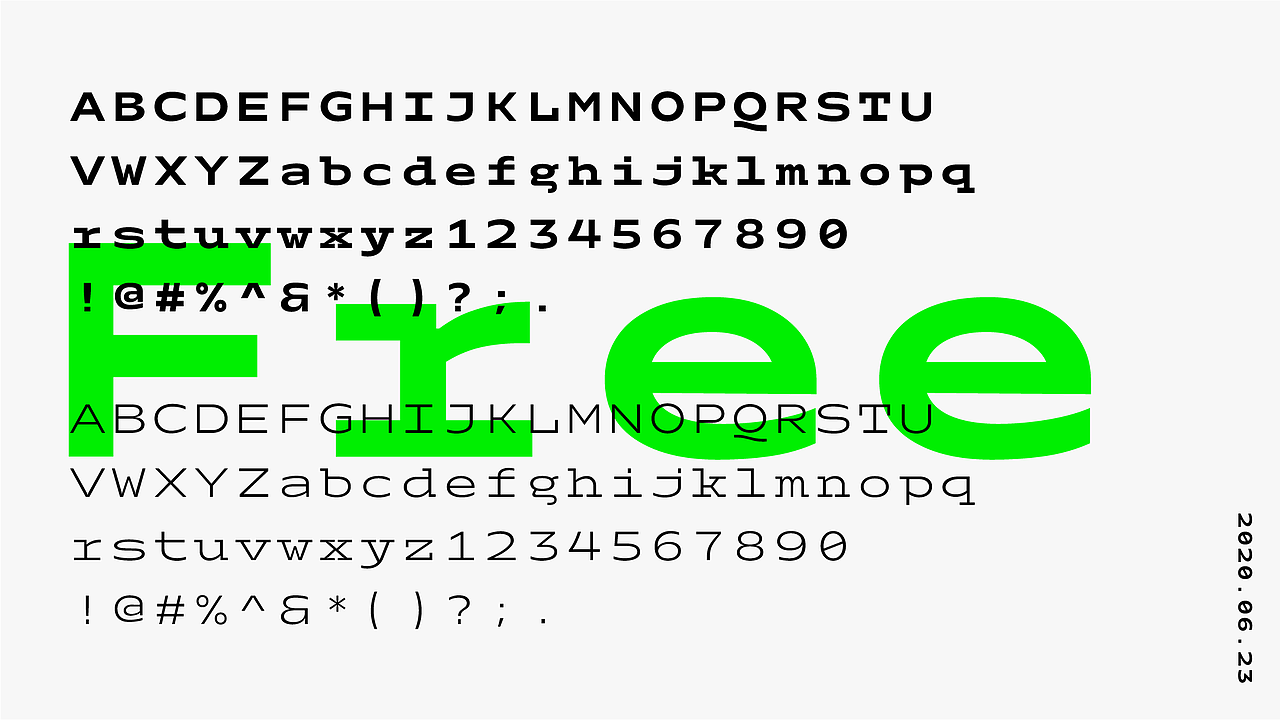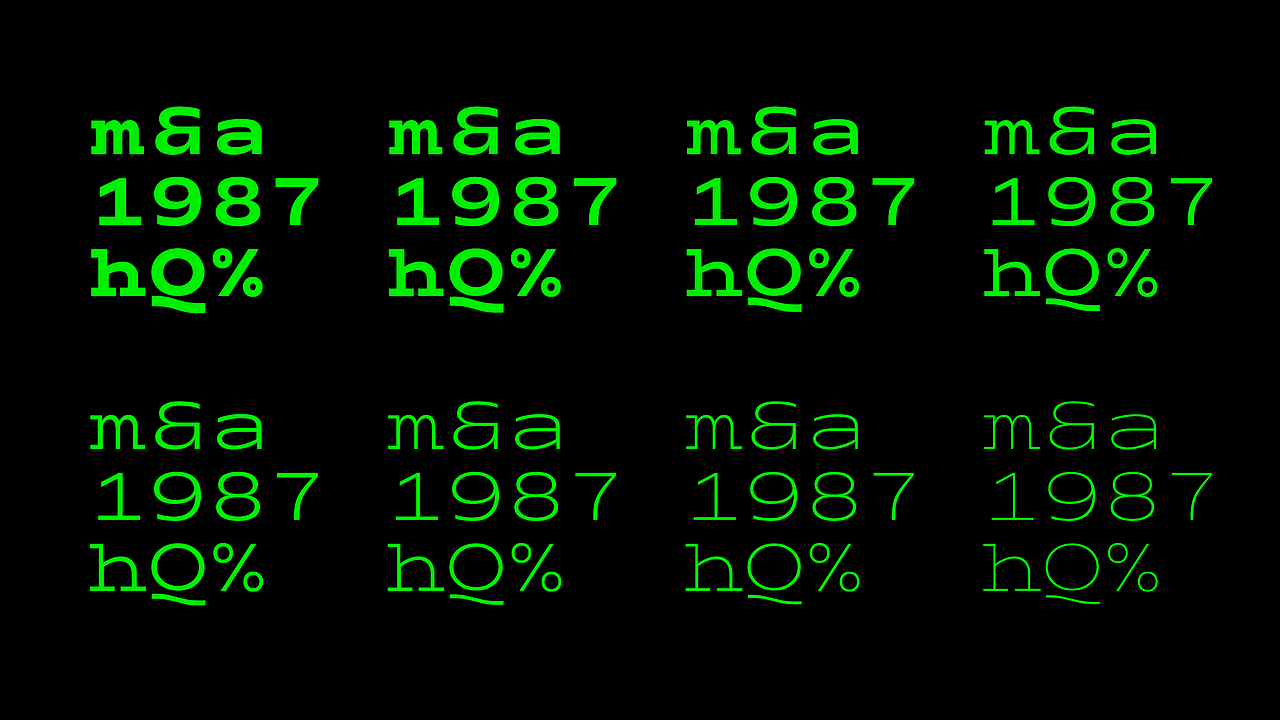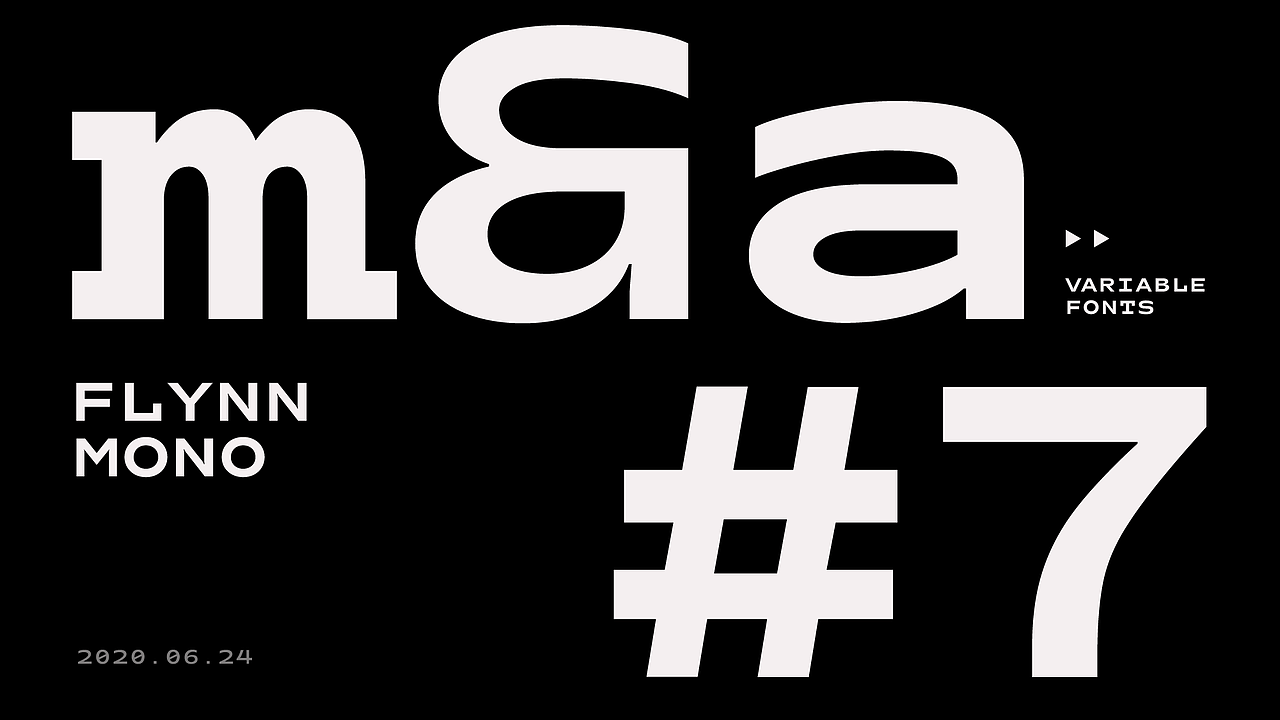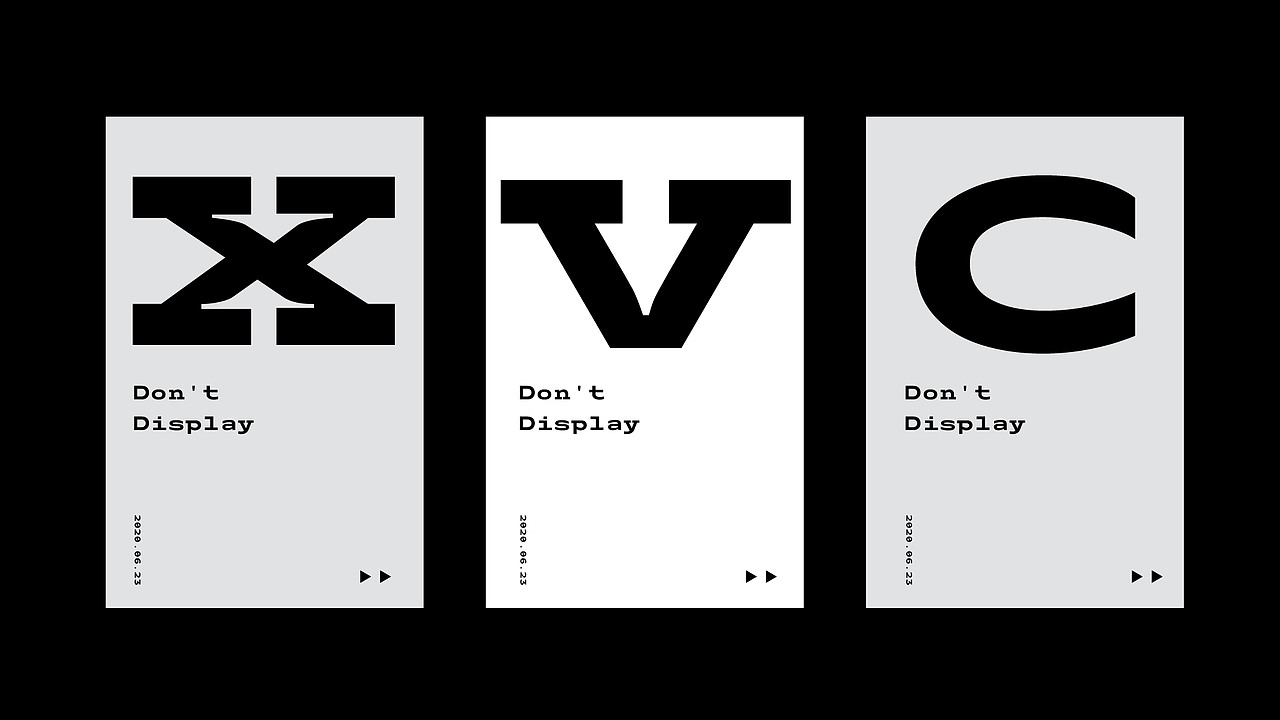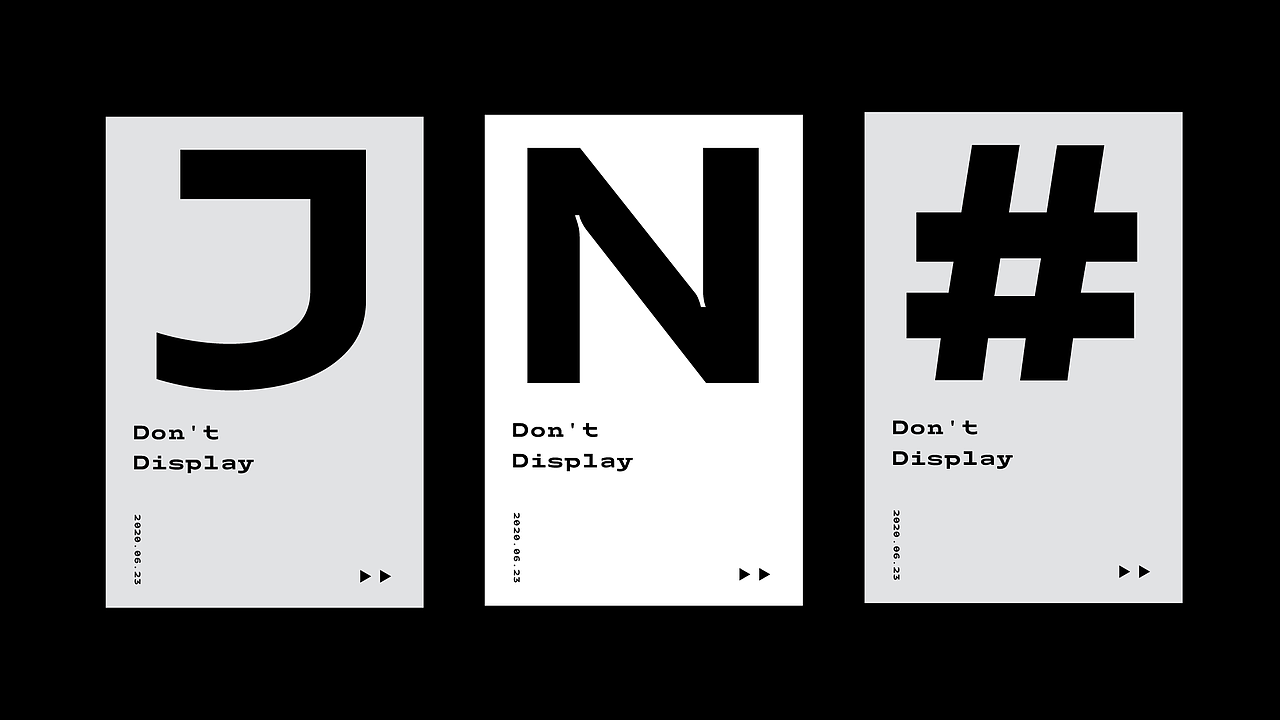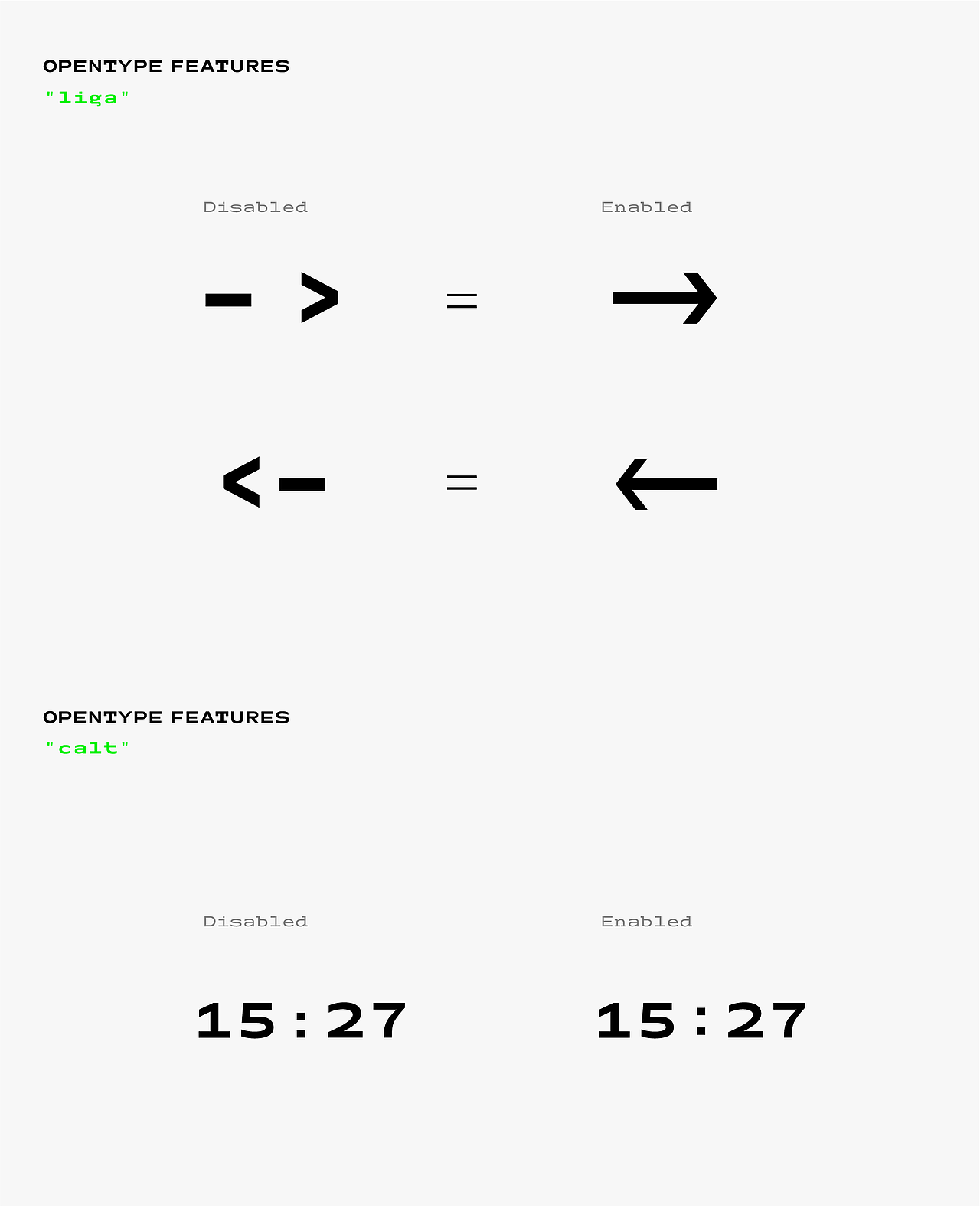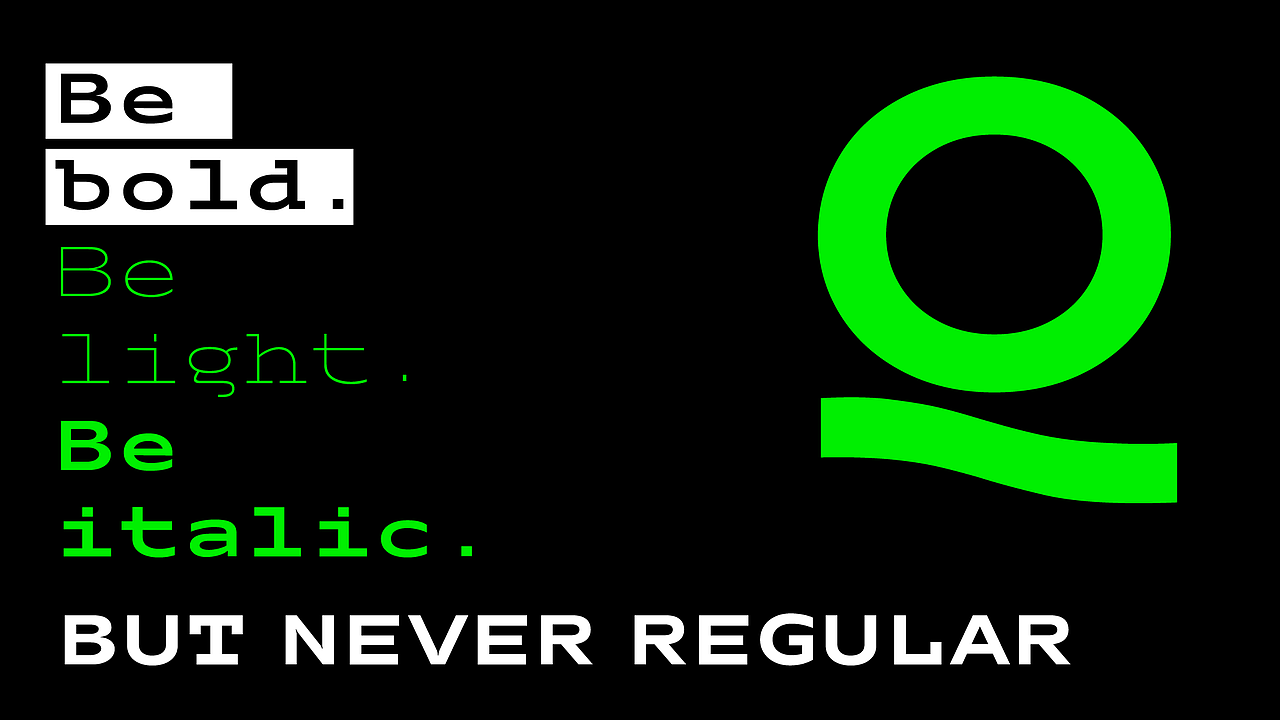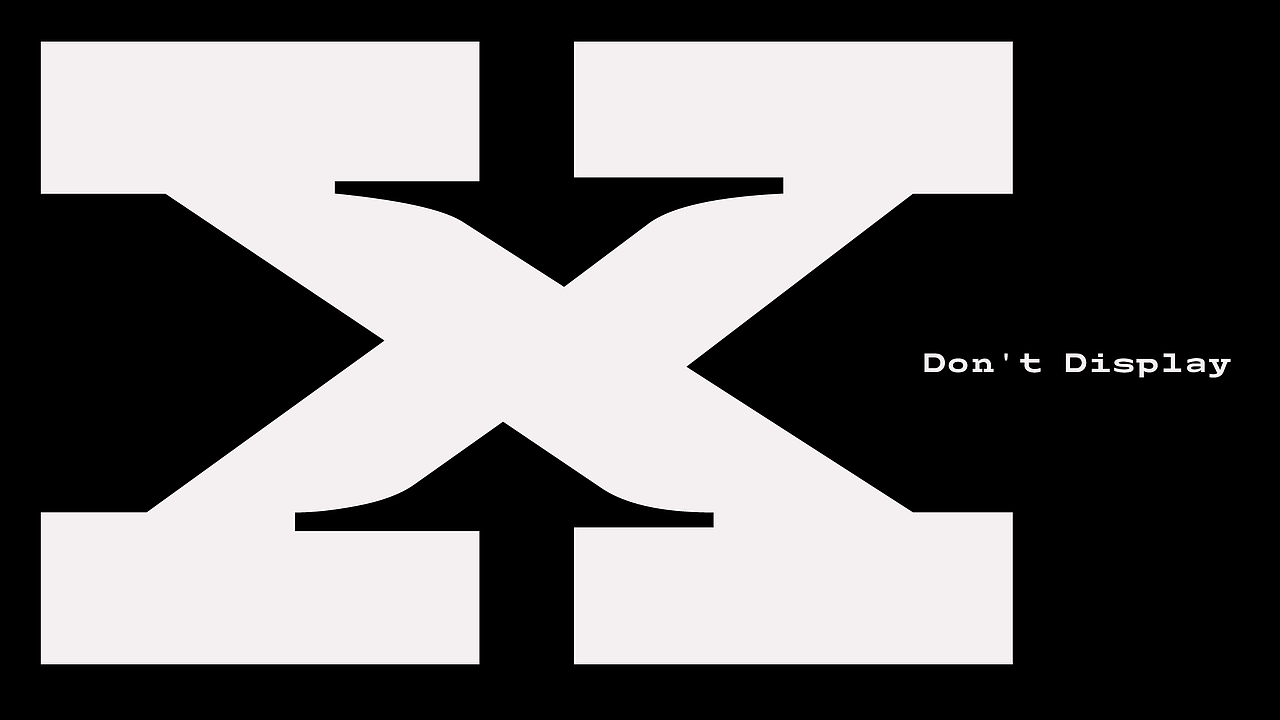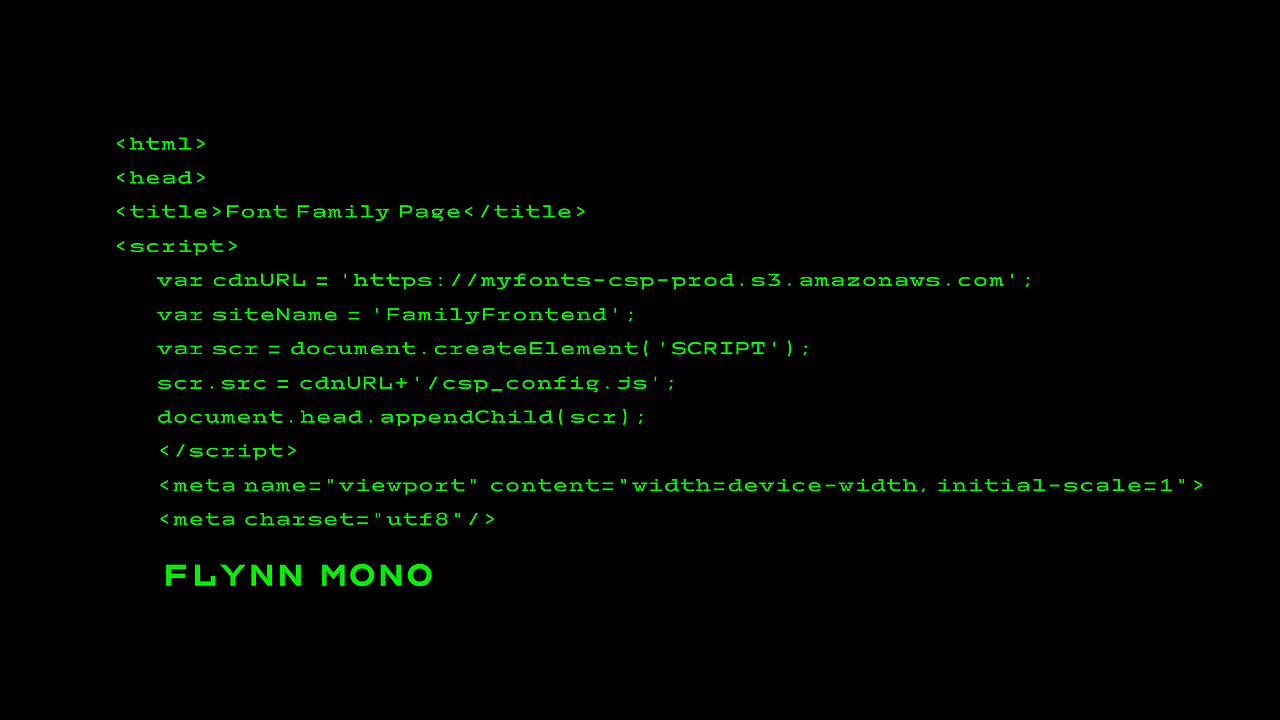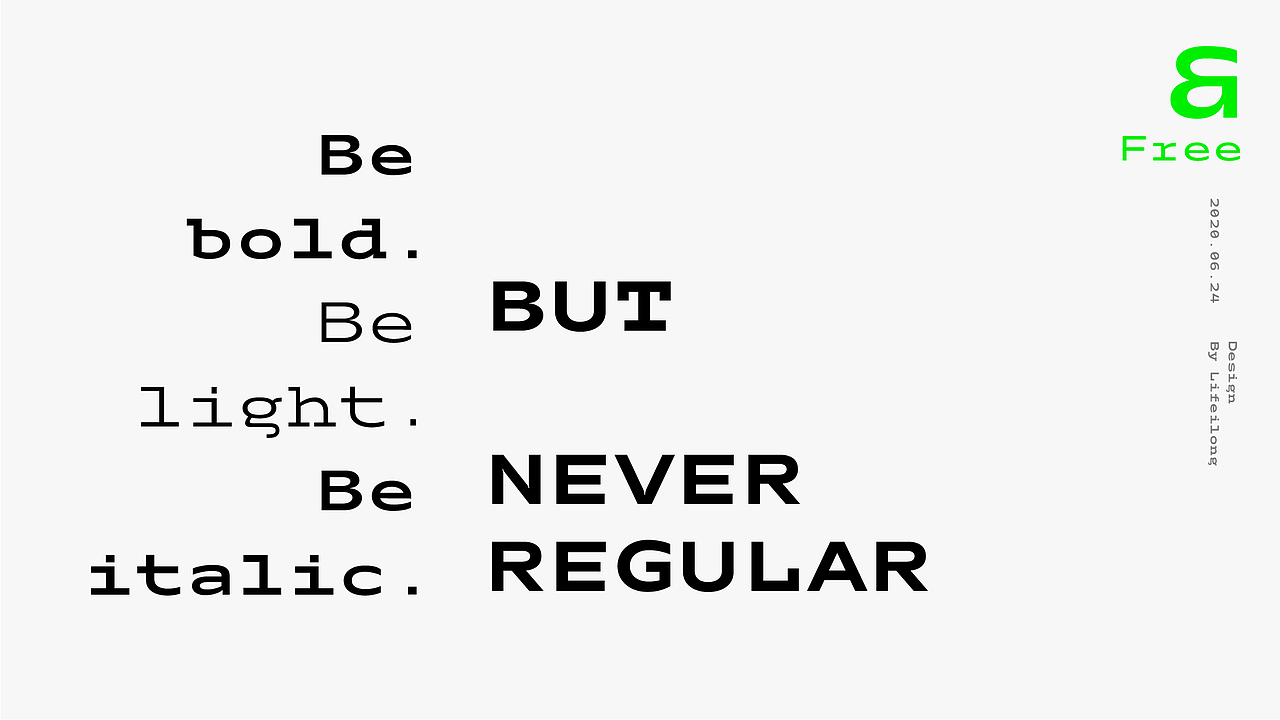
西文等宽字体 免费下载
最近设计得一款等宽西文字体 Flynn Mono 并做成了可变字体
造型比较怪异,加个比较夸张的屏显化处理,但并不适合用做正文阅读
也不适合拿来敲代码用…
主要还是想研究下Opentype features ..
两个小特性 自动生效
输入-> 即可生成箭头符号
注意观察冒号的位置